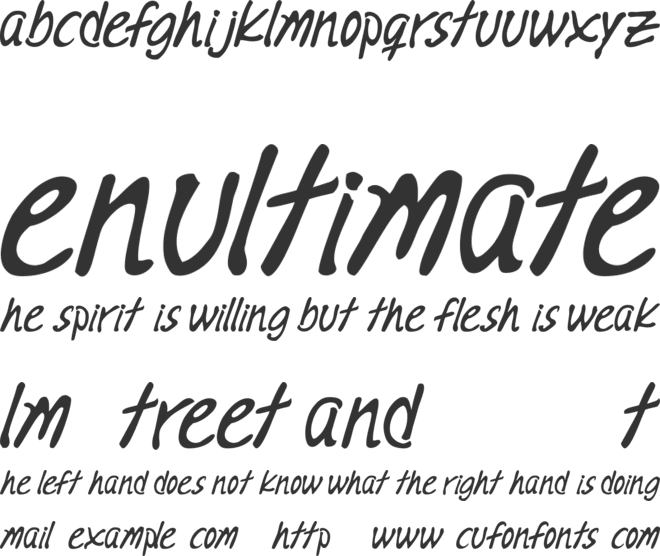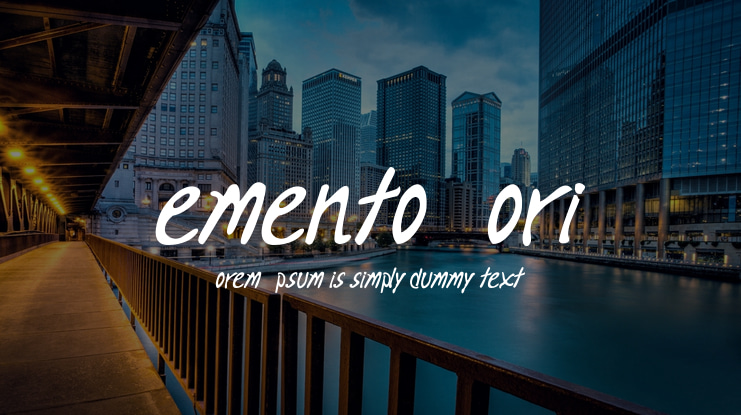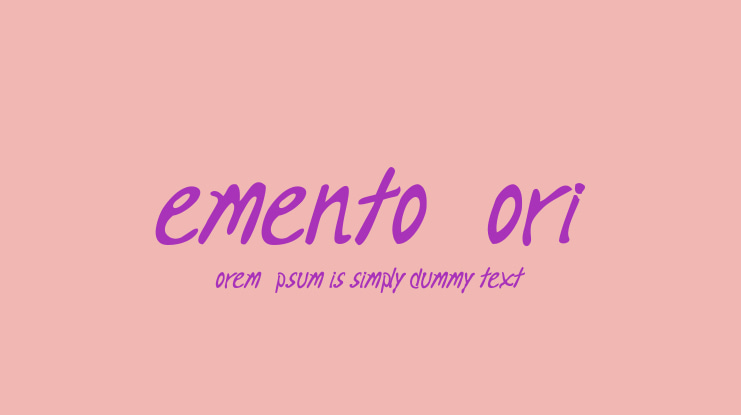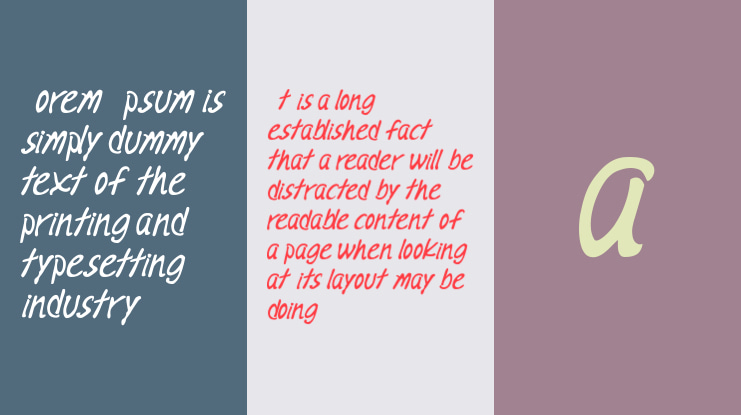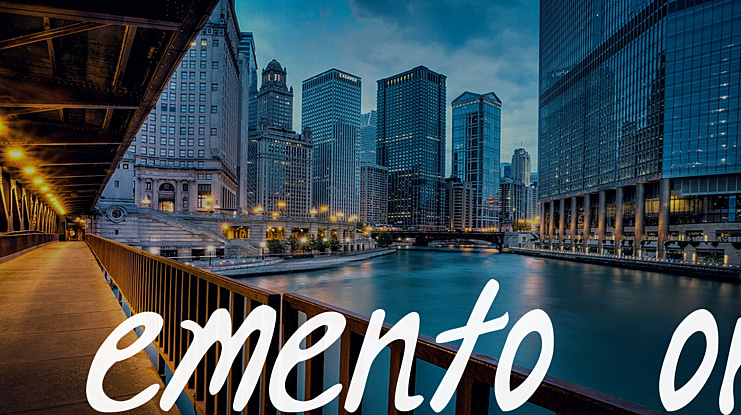
Memento Mori Font
Maria Jose Cuevas Canto
Tipografía sacada de la caligrafía de una persona sentimental...Contiene Caracteres en Minusculas de la a-z y vocales acentuadas, apenas esten los numerales se haran las correciones correspondientes. Su nombre: waffles